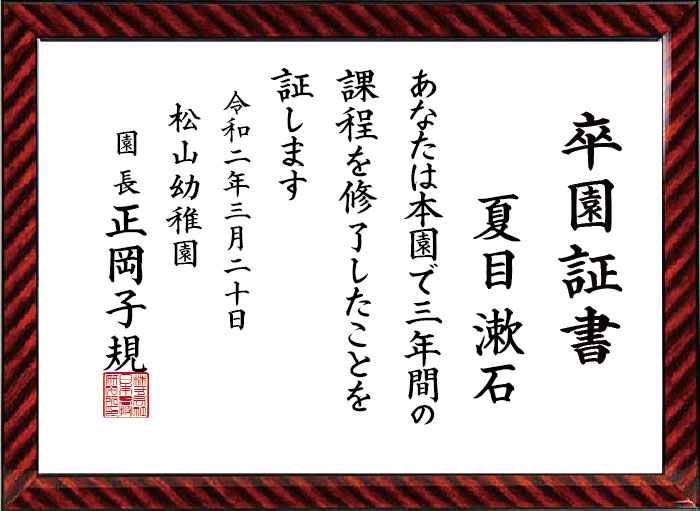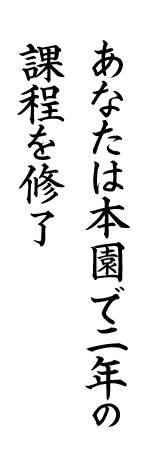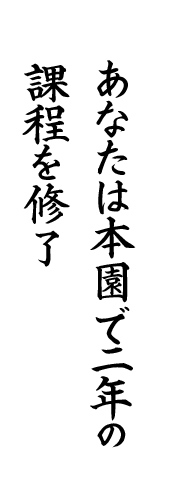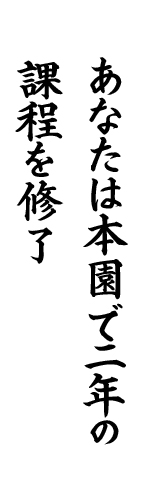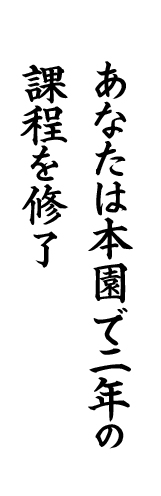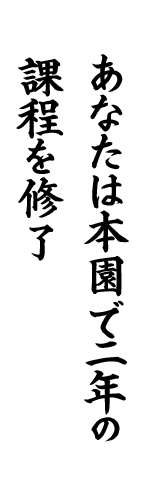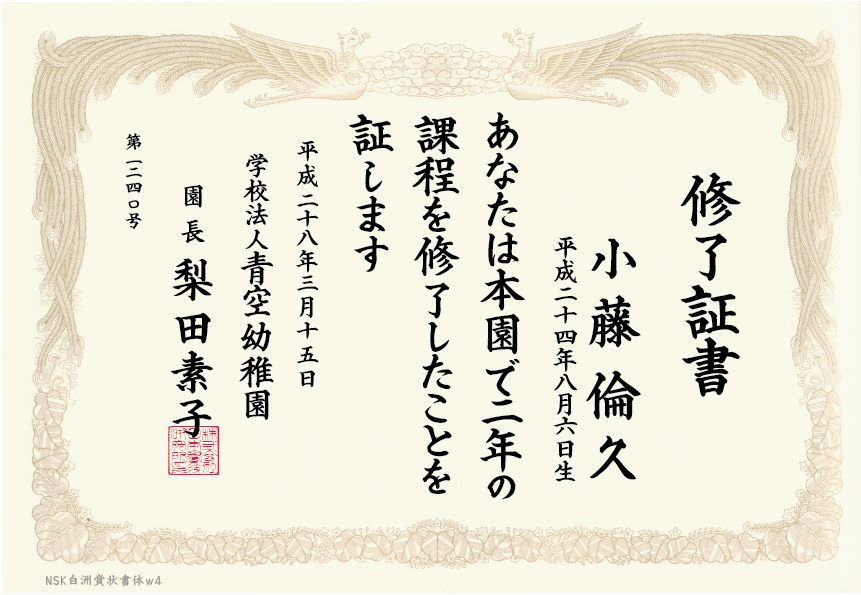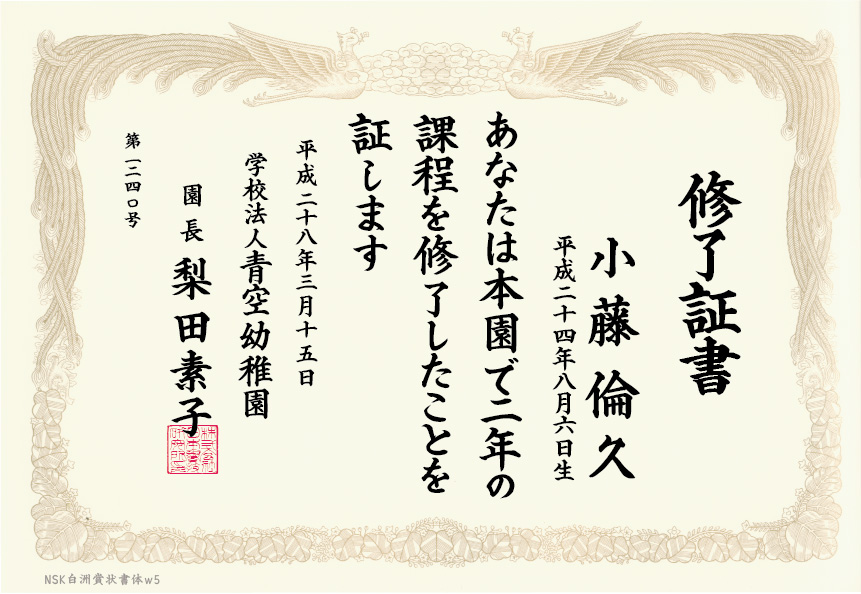
保育園、幼稚園様は この賞状作成専用フォントで職員さんで簡単にプロ級の卒園証書が作れます
この賞状専用フォントを利用して多くの幼稚園、保育園様で
卒園証書をお作り戴いております。
貴園の職員にて、下記に様な美しく,格調高い賞状が作成出来ます。
,賞状作成のための外注費の削減を進めるとともに、園児のために、日頃の頑張りに対して
手軽に、努力賞や頑張りました賞などを作ることが出来ます。
賞状の線の太さもいろいろと用意されています。
白洲賞状書体W1にて作成
本文:あなたは本園で2年の課程を修了したことを証(し)ます
白洲賞状書体W2にて作成
本文 『証します 』 の『し』をご覧ください 。違う表現の『し』が使われています。全てのひらがなに対して、表現を少し変えた 書体を用意して、いかにも手書き感を表現できるようにしています。
白洲賞状書体W3にて作成
白洲賞状書体W4にて作成
本文 『証します 』 の『し』をご覧ください 。違う表現の『し』が使われています。全てのひらがなに対して、表現を少し変えた 書体を用意して、いかにも手書き感を表現できるようにしています。
白洲賞状書体W5にて作成
この賞状フォントを利用しますと、貴方でも簡単にプロ級の美しい賞状が出来ます。
特長 A
| 特長1 | 賞状を手書きで書く時の書風で賞状フォントが作られていますので手書きとの違いが判りません。 |
| 特長2 | 賞状の表題様に別に表題フォントを用意した。 これにより本文の書体より文字表現を強くして、賞状を引き締めます。 |
| 特長3 | ひらがな、片仮名など別の少し異なる書体も用意され、同一文面の中で異なるひらがな表現が出来ます。 |
| 特長5 | 文科省小学校学習指導要領に準拠した、字形の賞状フォントも用意しています。 |
特長 B
| 特長1 |
フォントは線の太さを変えた賞状書体フォントを用意しています。 w1 : 通常揮毫時の線の太さ。 w2 : 通常揮毫時の線をやや太く。 w3 : 線をさらに太く。 w4 : 線をさらにもっと太く。 w5 : 線を最大に太く。 |
≪ 特長 1 ≫
| w1 | w2 | w3 | w4 | w5 |
≪ 特長 2 ≫
修了証書の様に賞状の表題様に別に表題専用フォントを用意して、出来栄えを更に良くします。
(タイトルに相当しますので、少し力強い書風にて表現された、フォントが用意されています。)
≪ 特長 3 ≫
ひらがな、片仮名など少し異なる書体を用意しております、かな文字を違った表現を可能にして手書き迫った
この賞状専用フォントを利用して多くの幼稚園、保育園様で
卒園証書を作り,賞状作成のための外注費の削減を進めるとともに、園児のために、日頃の頑張りに対して
手軽に、努力賞や頑張りました賞などを作ることが出来ます。